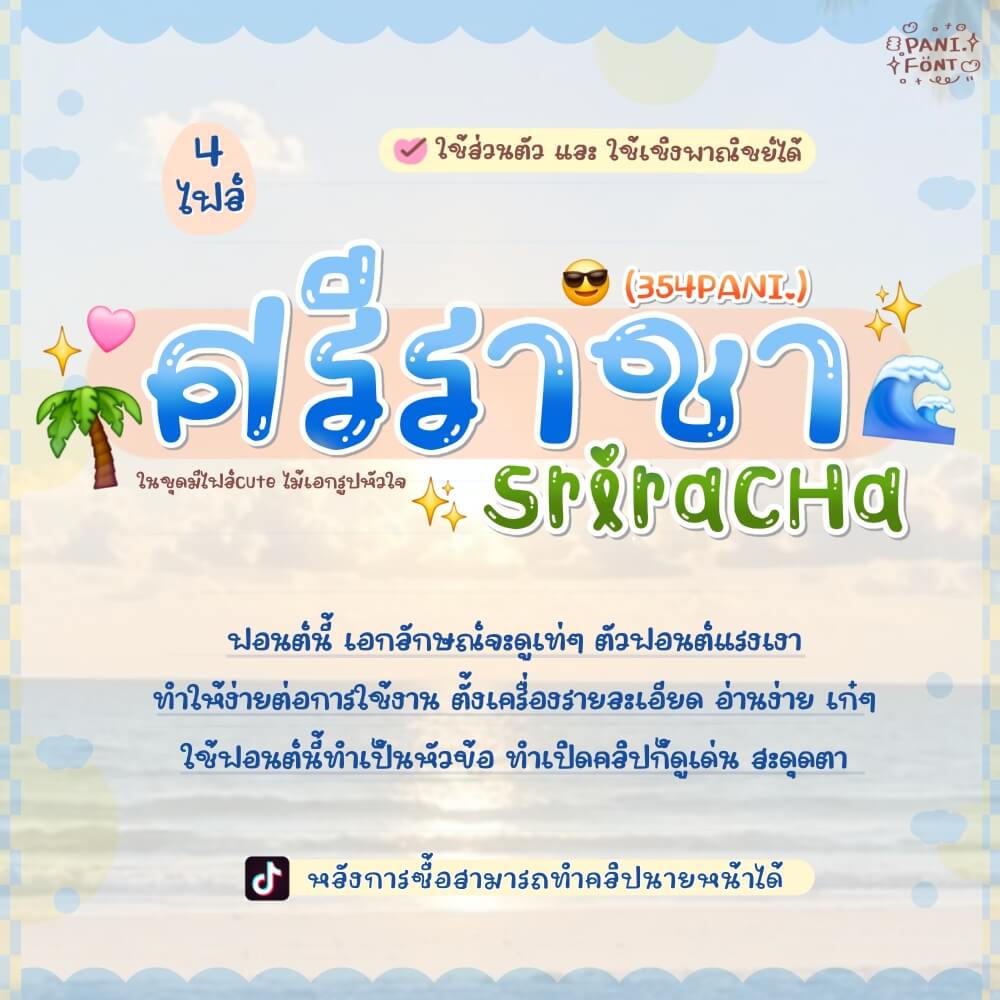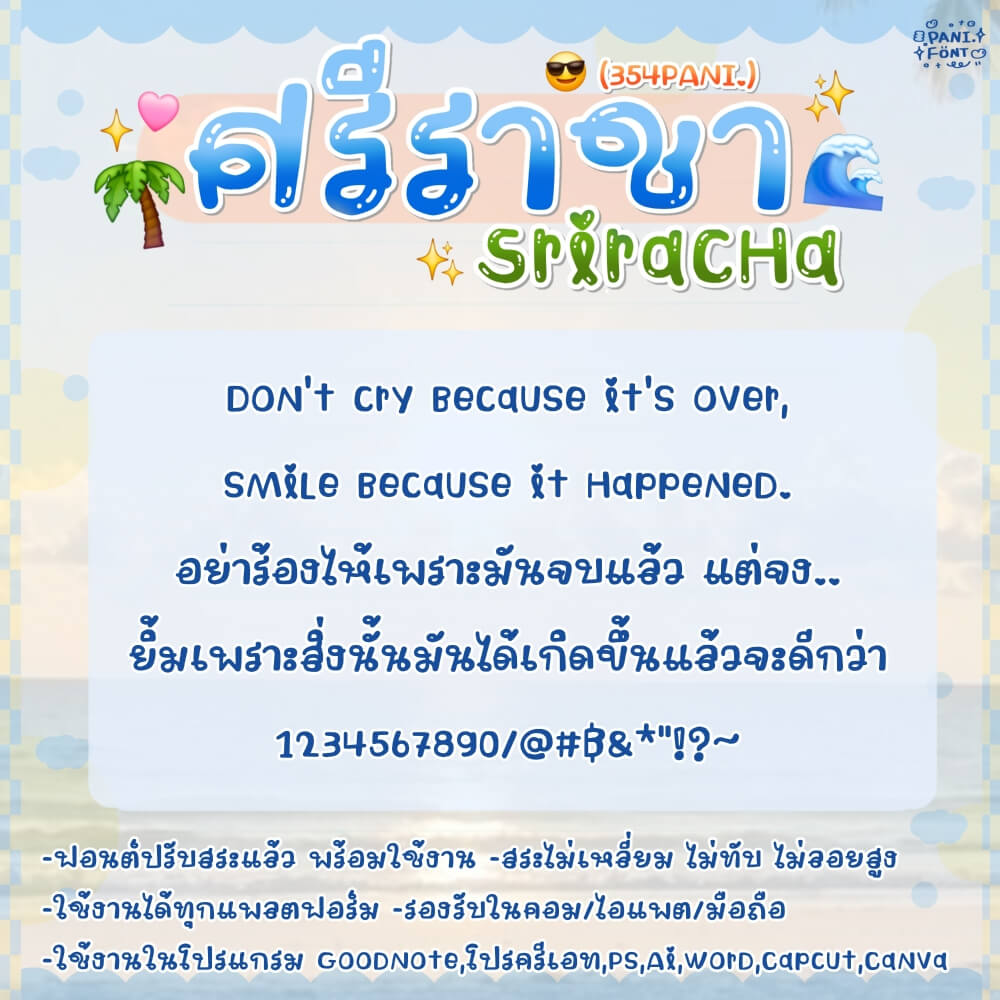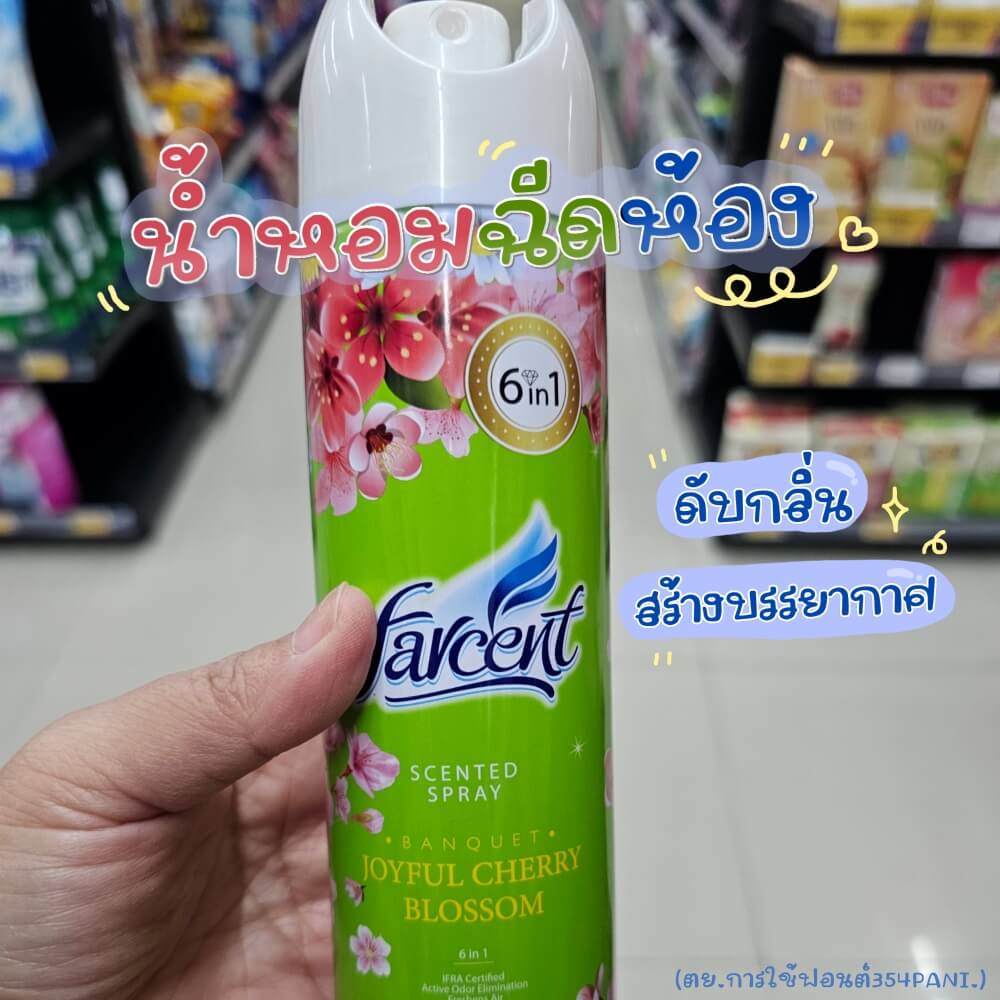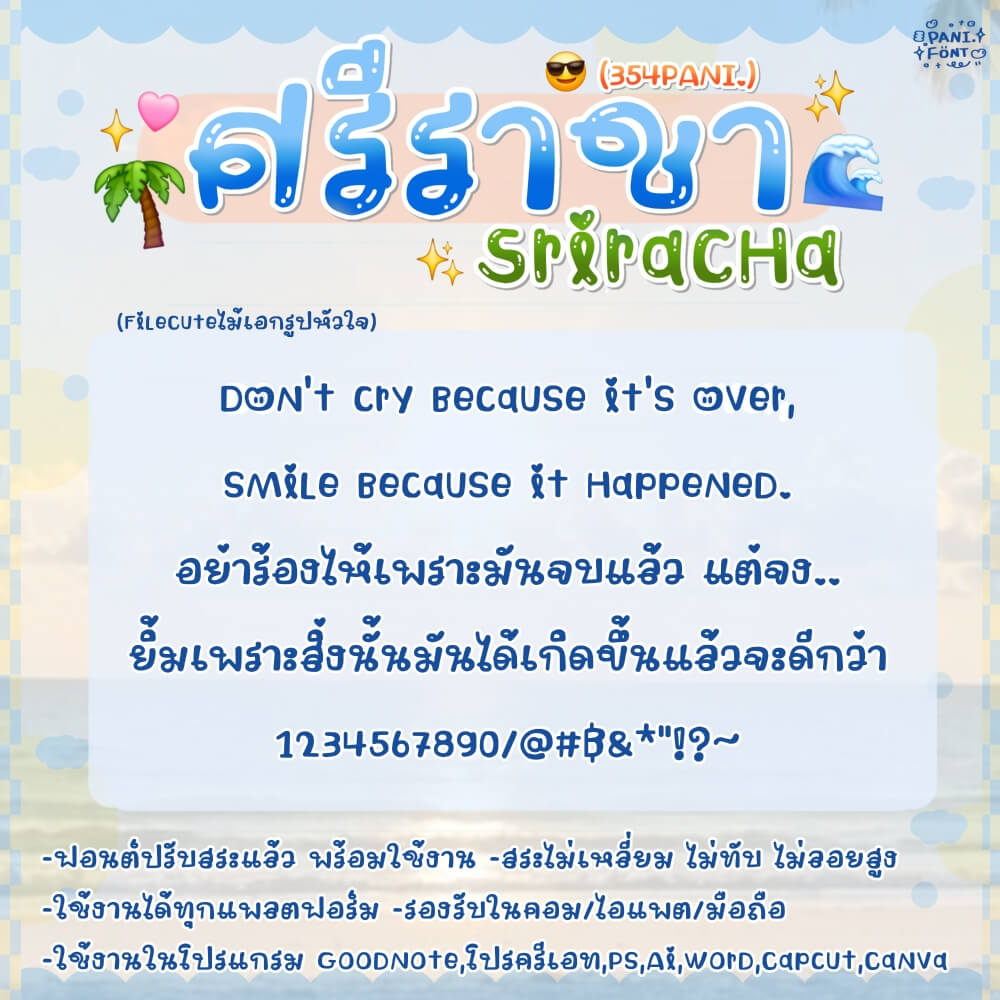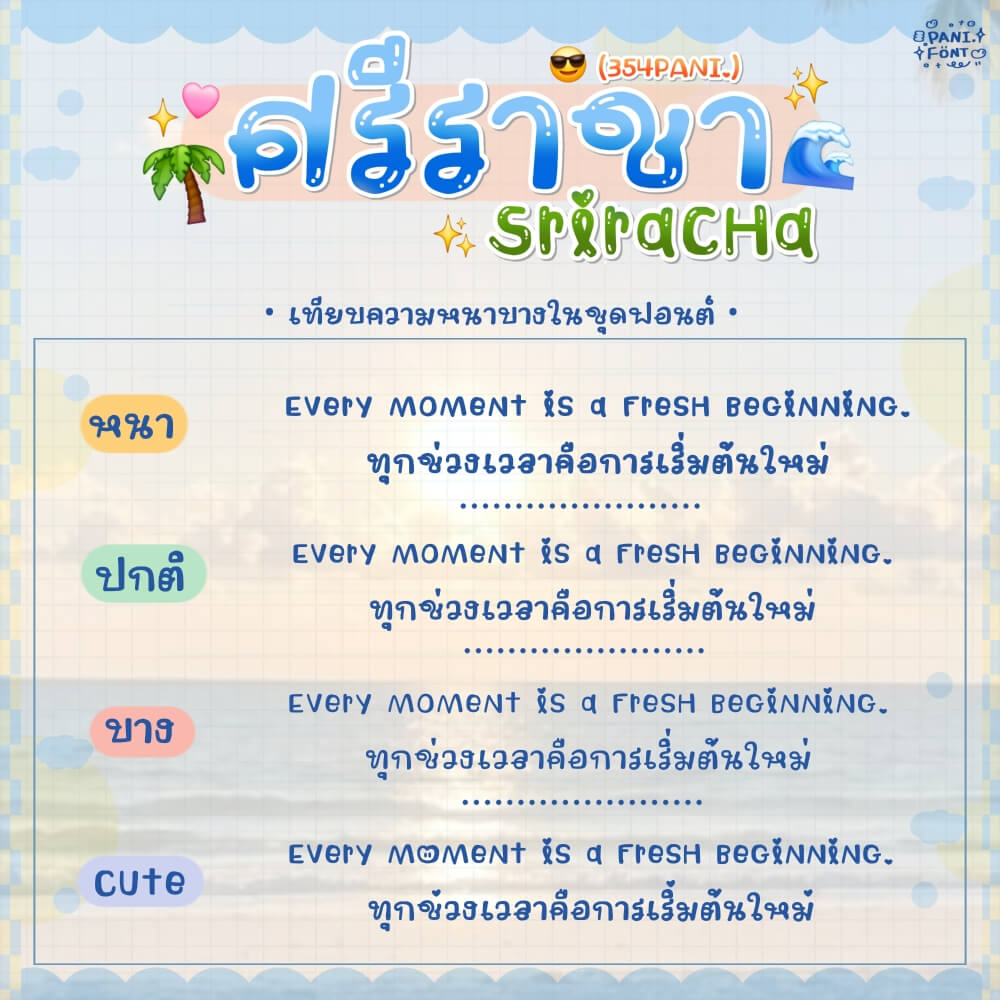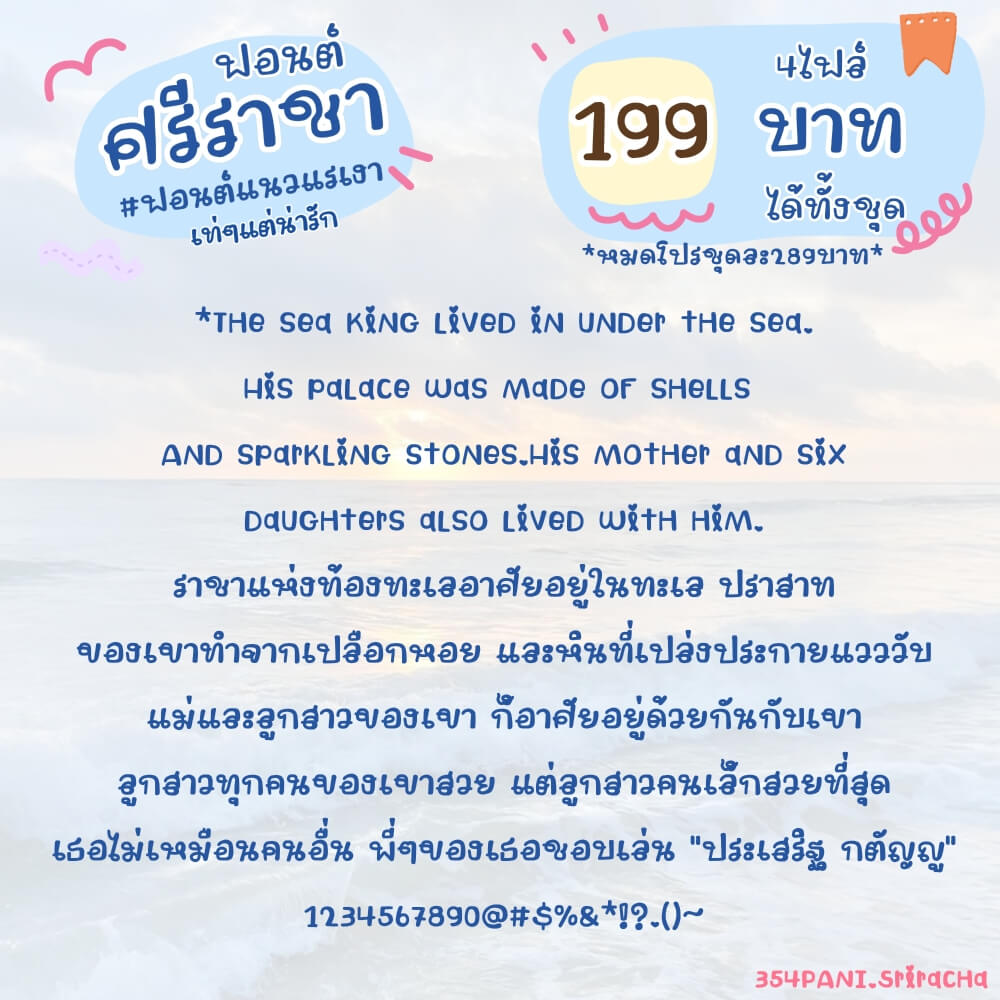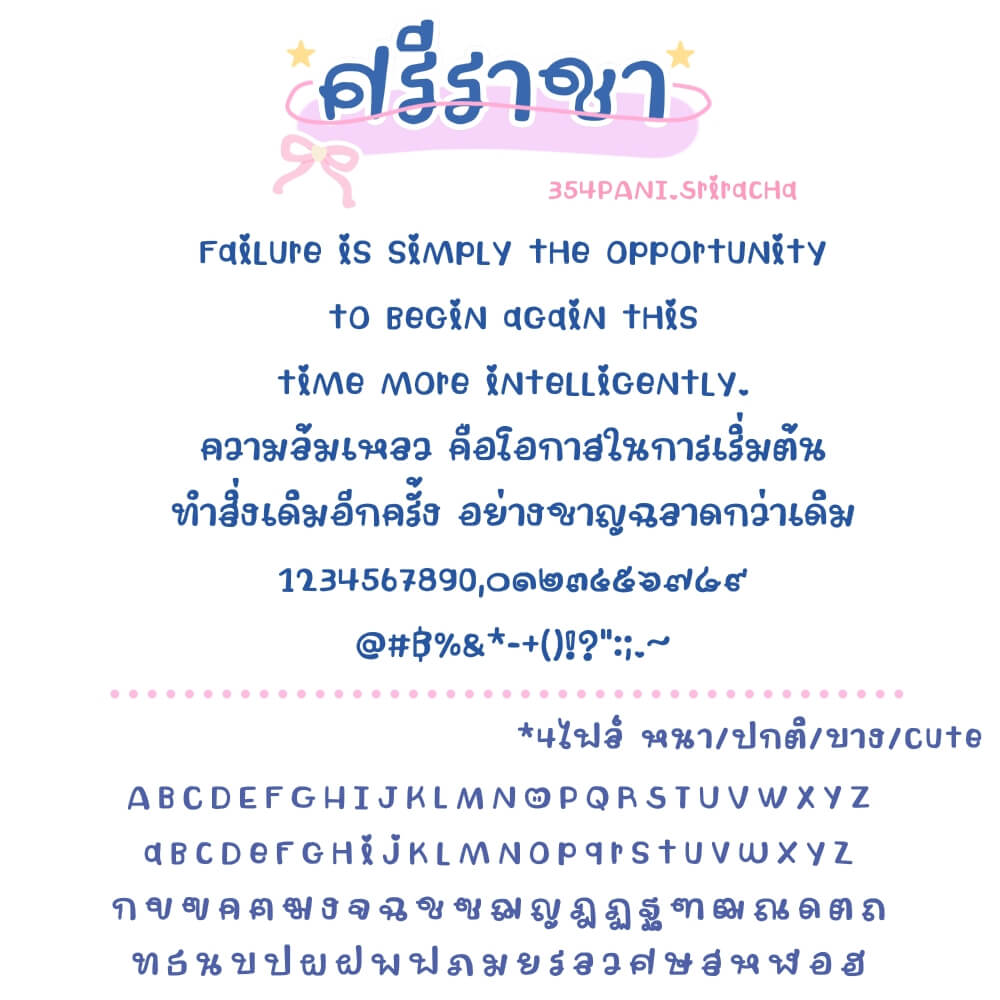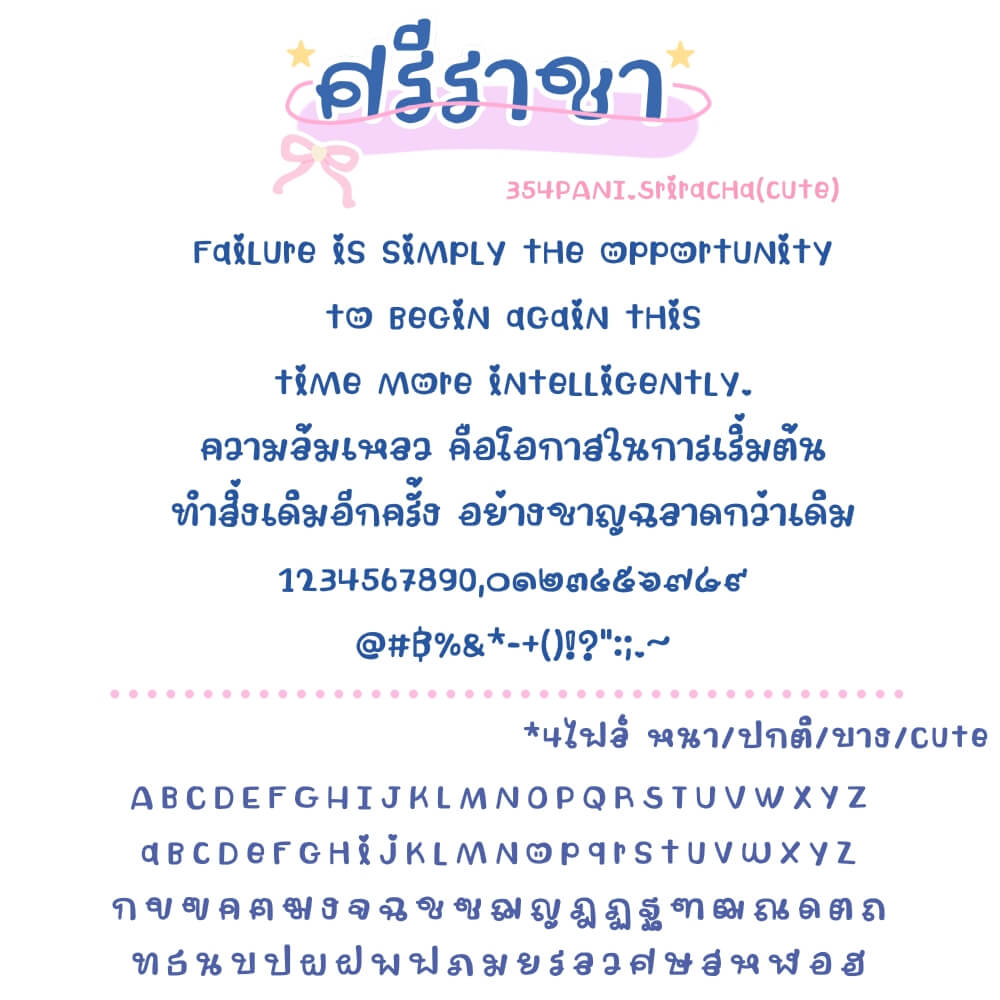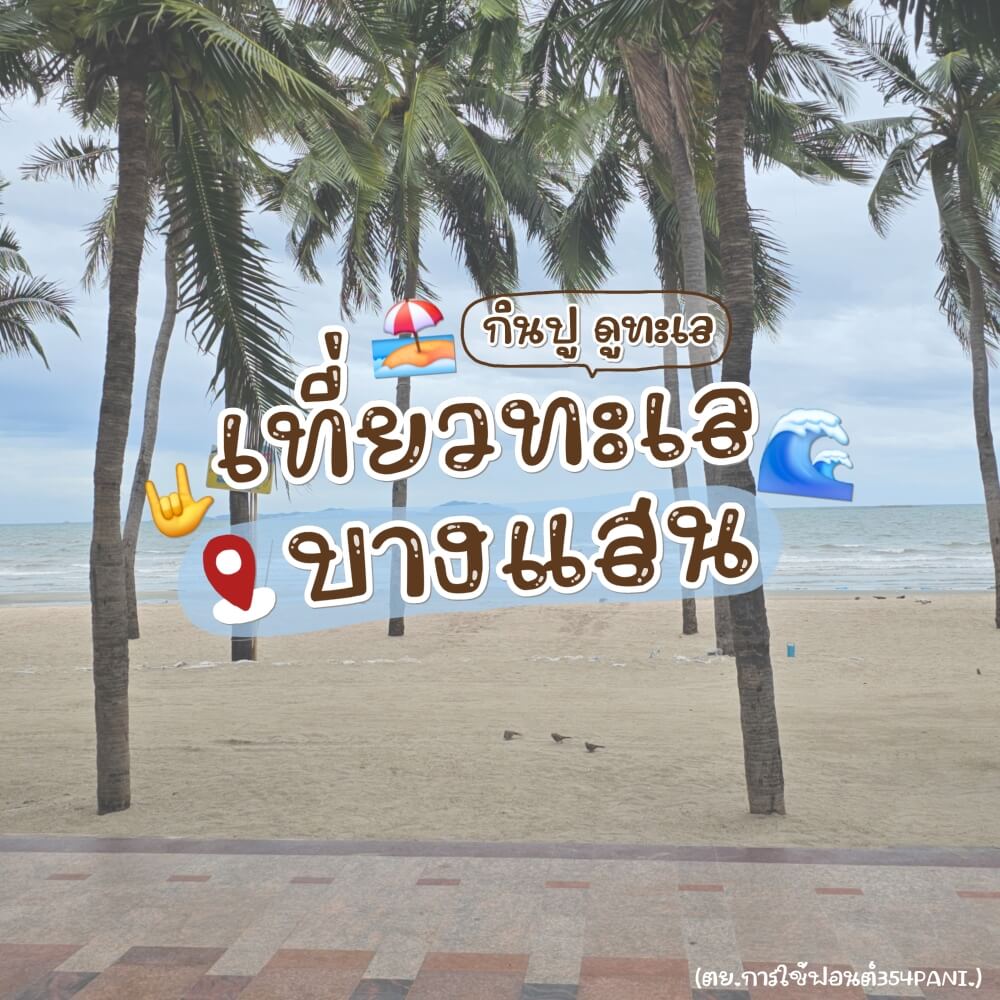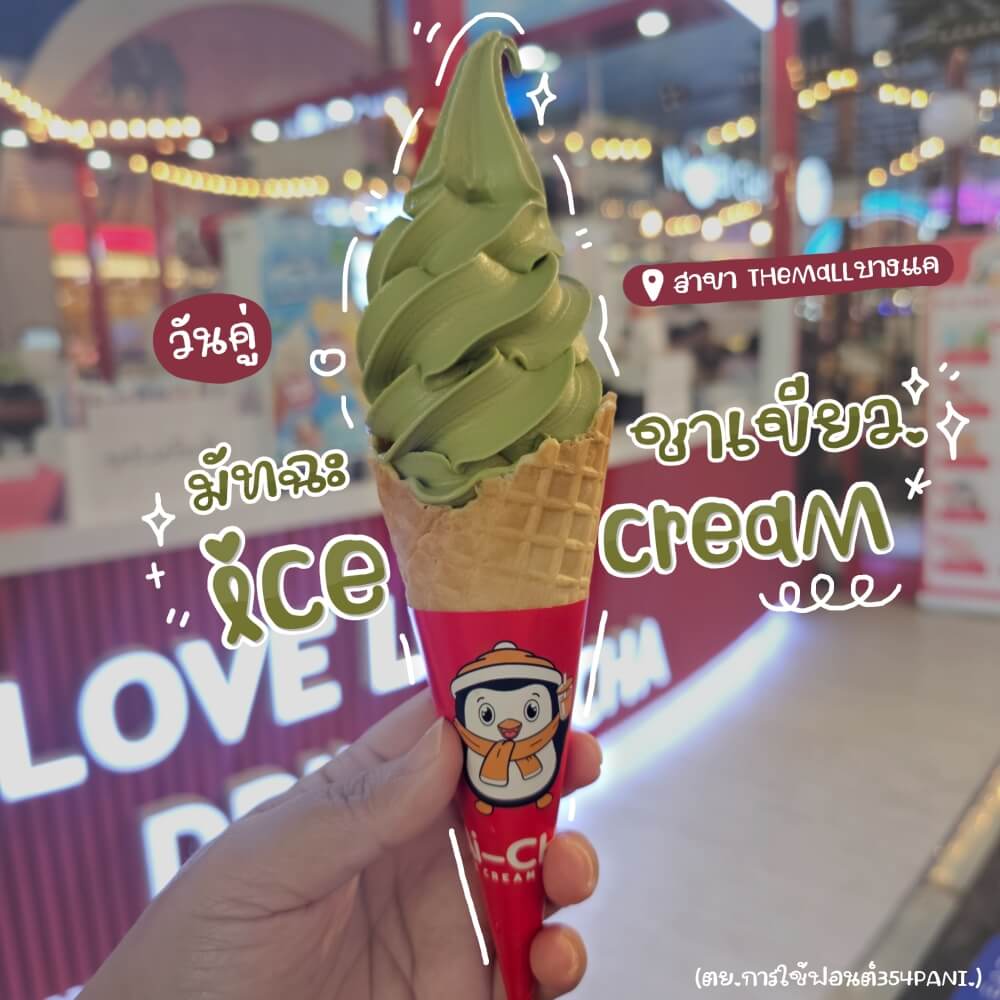
354PANI.ศรีราชา
ฟอนต์ 354PANI.ศรีราชา – จะแต่งปกคลิป แต่งรูปก็สวยมาก แนะนำเลยค่ะ ฟอนต์นี้ เอกลักษณ์จะดูเท่ๆ แต่การแรเงาในตัวฟอนต์ ทำให้ง่ายต่อการใช้งานและการใช้งานรายละเอียด ตั้งเป็นฟอนต์เครื่อง ก็ดูเก๋ๆ สวยงาม ใช้งานใน Good Notes ก็ใช้ฟอนต์นี้ทำเป็นหัวข้อได้ด้วยค่ะ
ชุดนี้ค่อนข้างครอบคลุมการใช้งาน แนะนำค่ะ